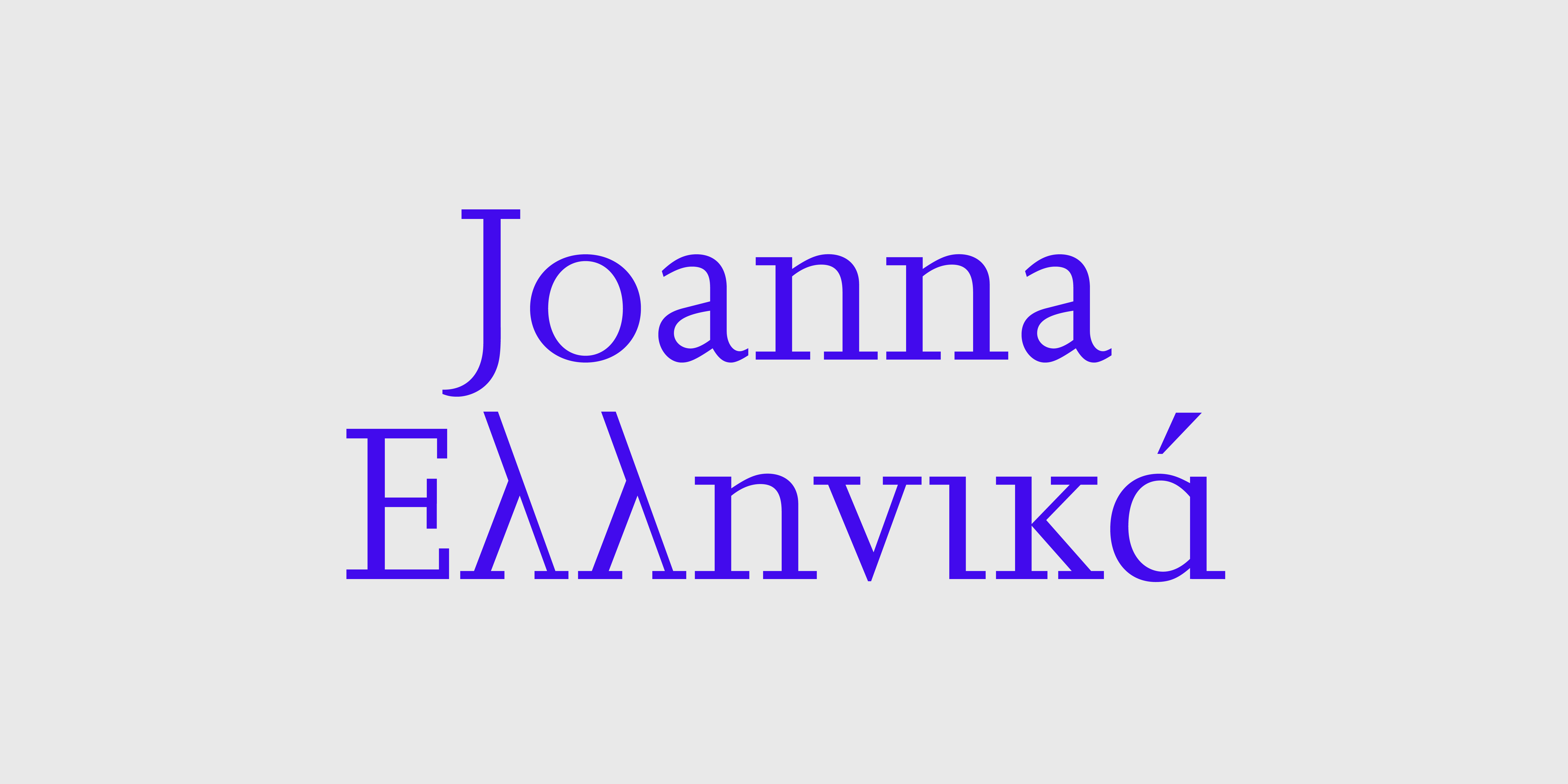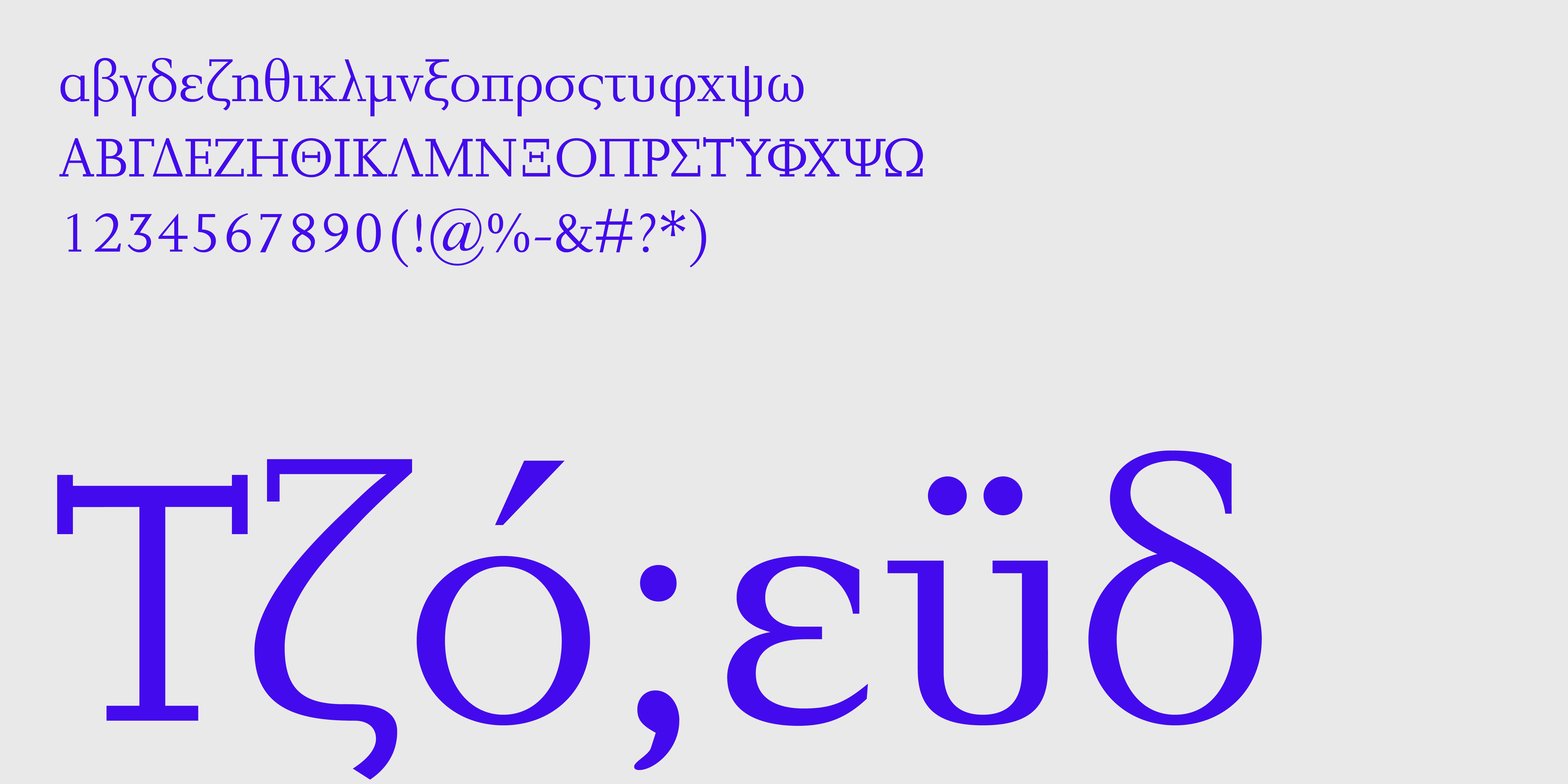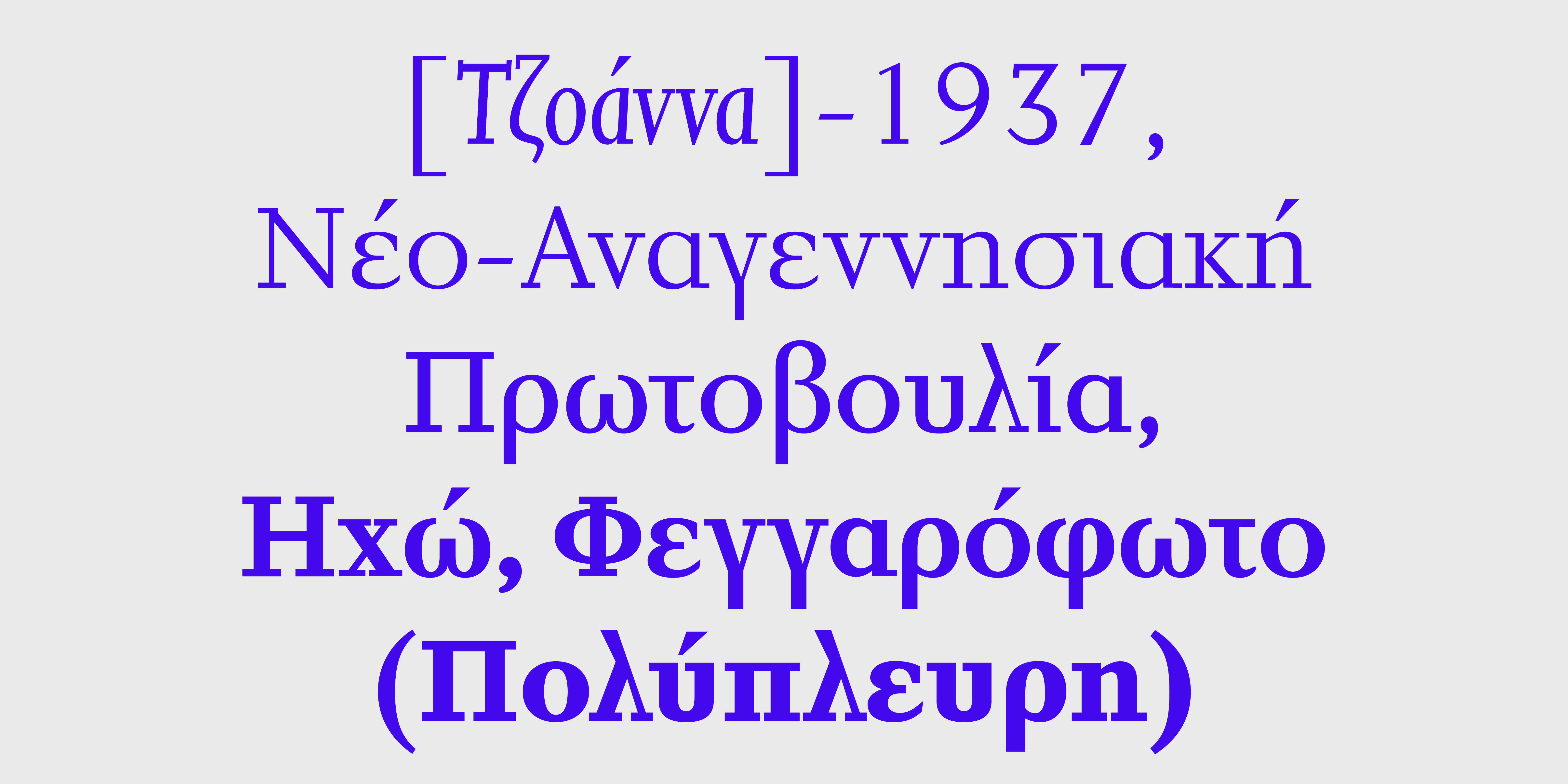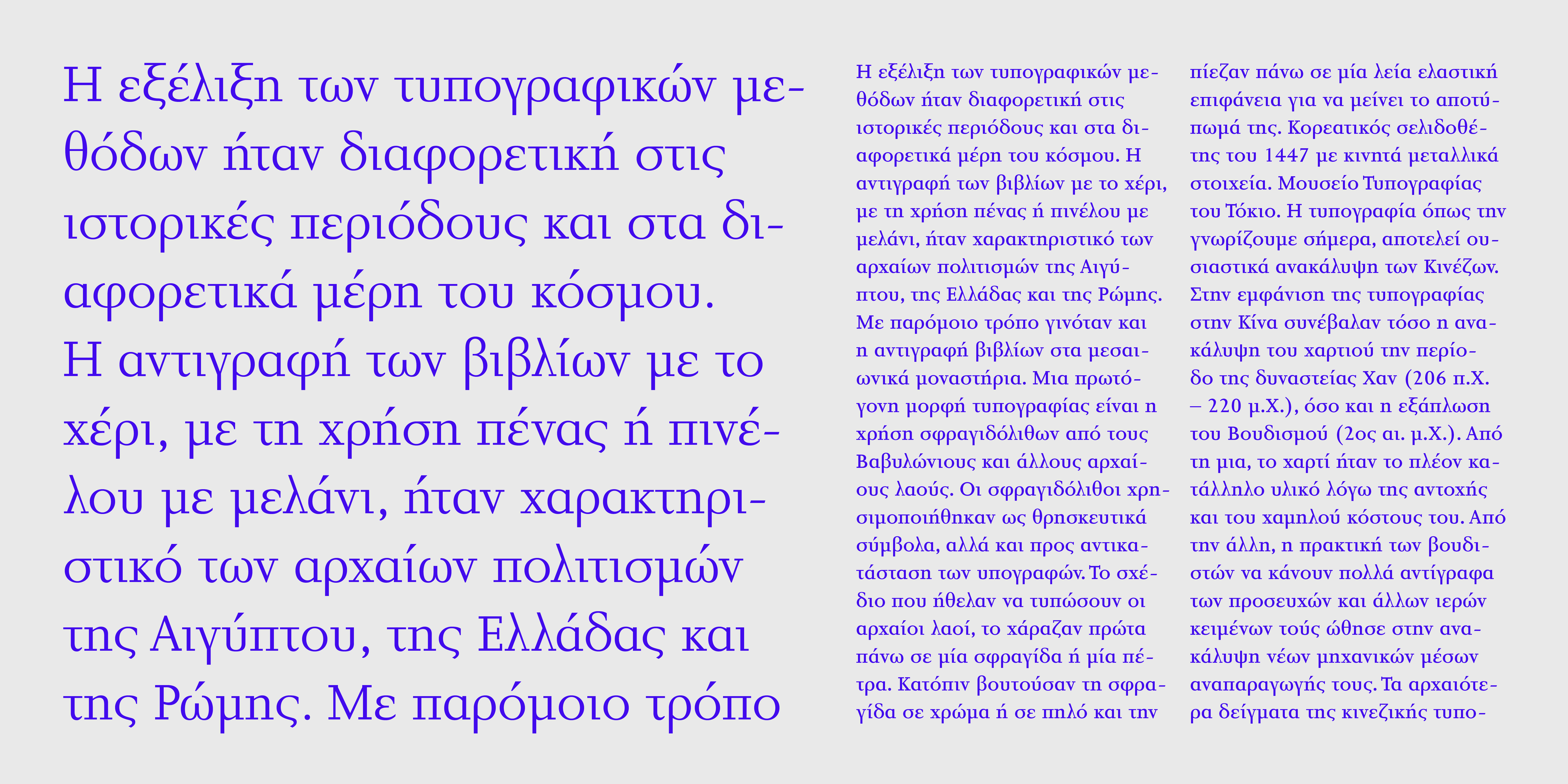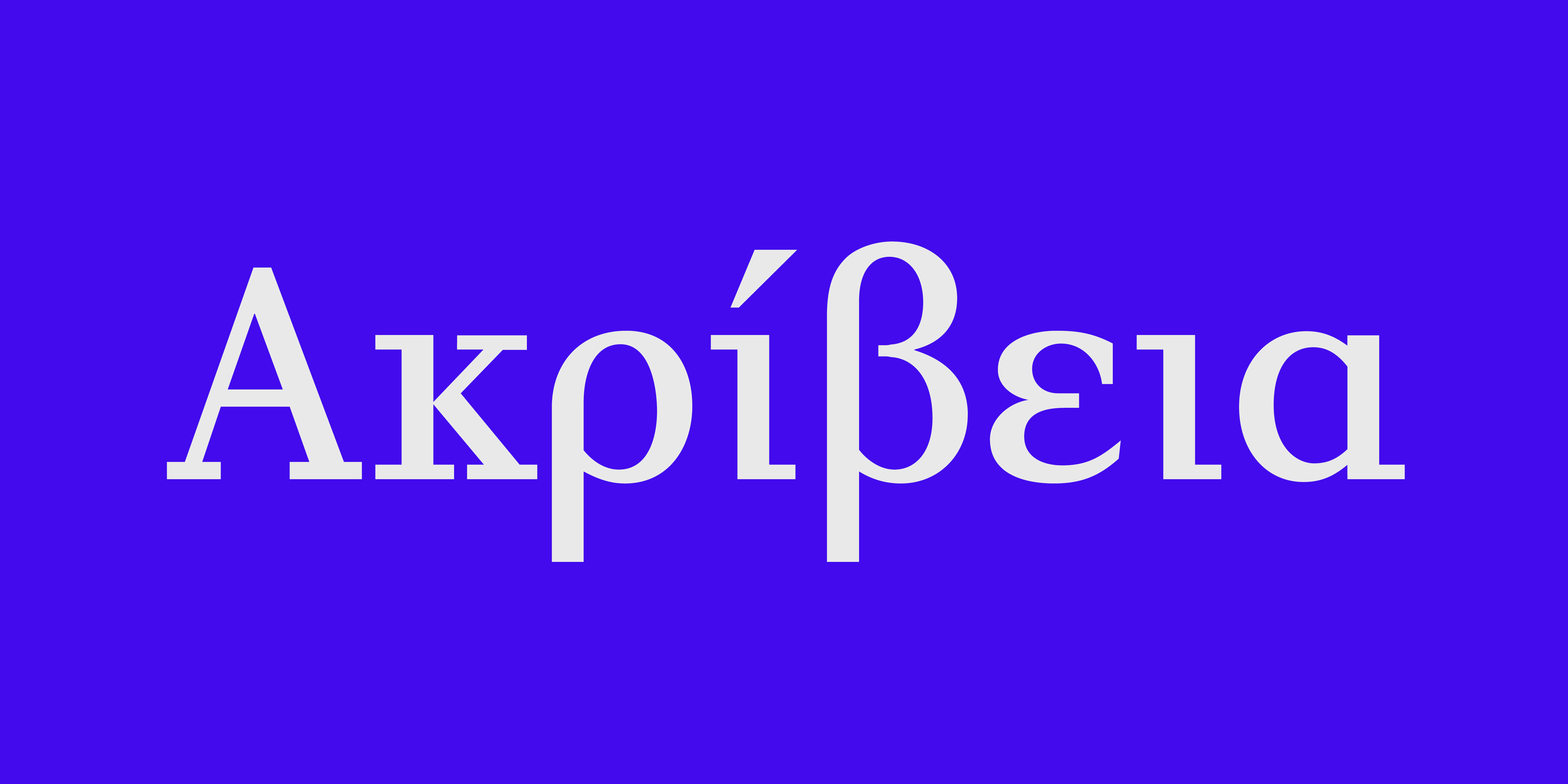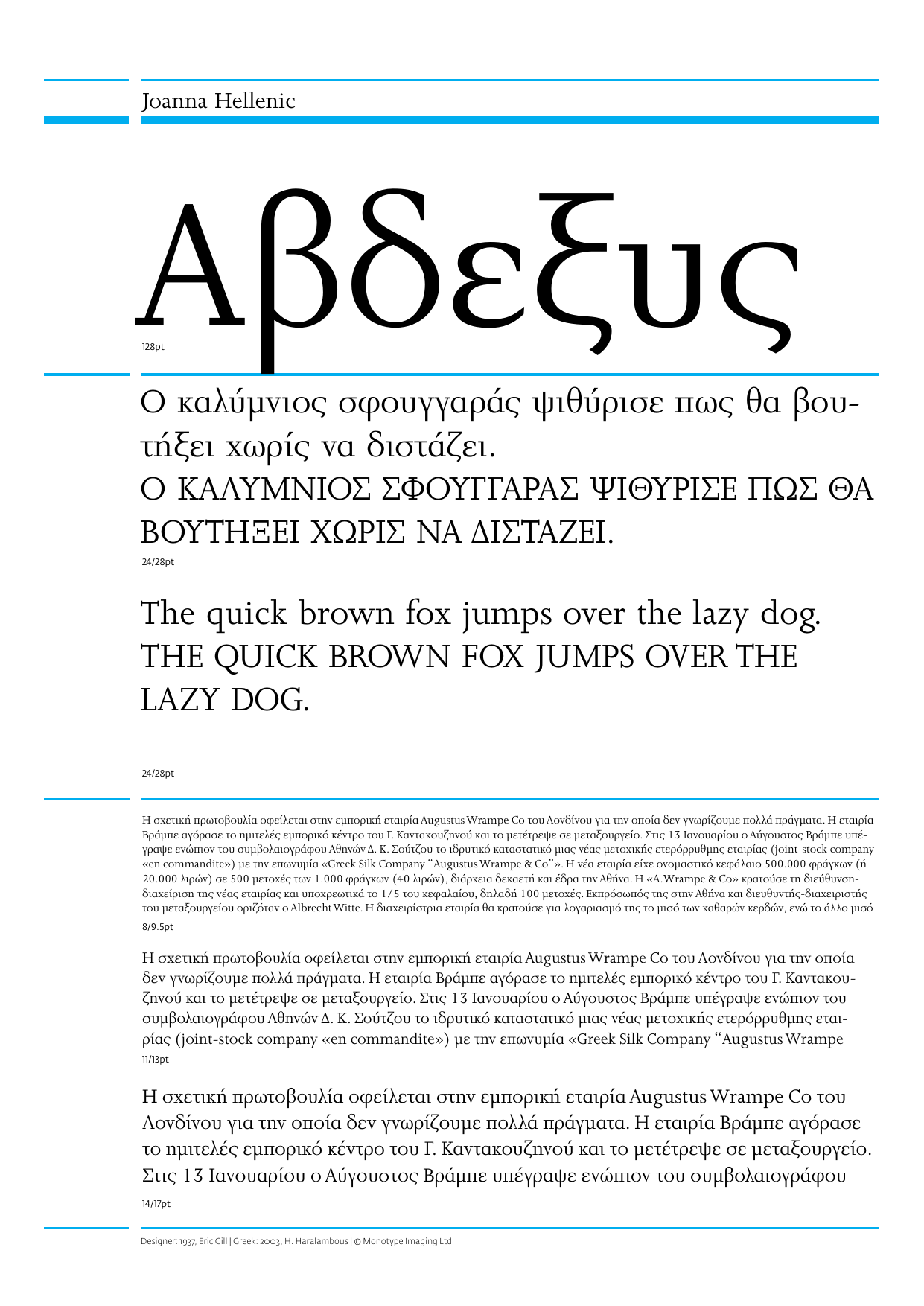
Joanna Ελληνικά
Η γραμματοσειρά Joanna δημιουργήθηκε από τα τυπογραφικά στοιχεία “Joanna Press” και αποτελεί μέρος της Νέο-Αναγεννησιακής παράδοσης του William Morris. Είναι χαρακτηριστικοί οι σχεδόν διαγώνιοι και ασυνήθιστα μικροί πλάγιοι χαρακτήρες. H Joanna είναι μια πολύπλευρη και εξαιρετικά αναγνώσιμη γραμματοσειρά.